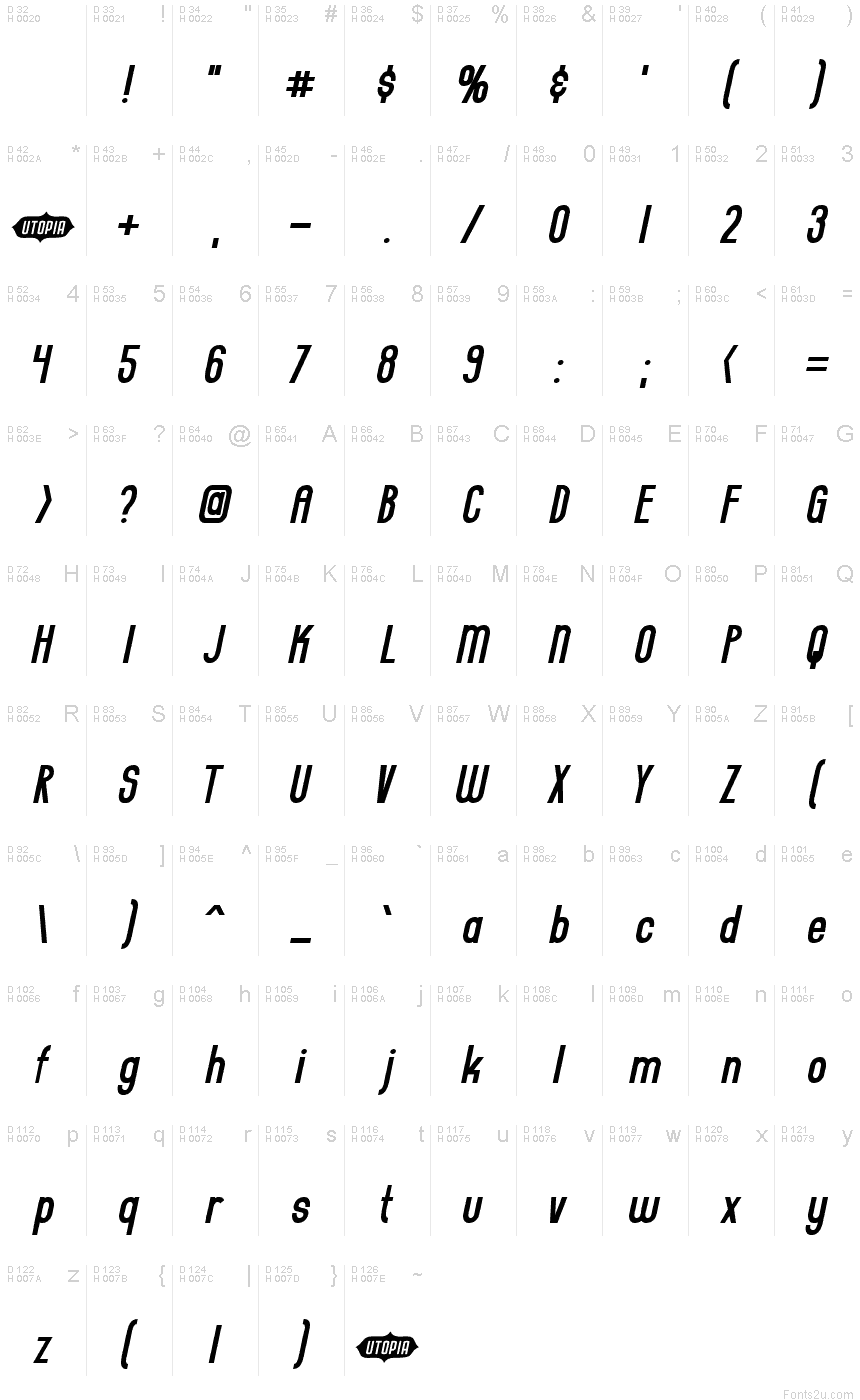
Everyday Formula Gaunt Sway
Everyday Formula Gaunt Sway od Utopiafonts to darmowy krój bezszeryfowy o ostrym, dynamicznym nachyleniu, który sprawia wrażenie, jakby był w ciągłym ruchu. Wysokie, smukłe litery i ciasna, pochylona do przodu postawa tworzą wrażenie dynamiki, jakby każde słowo pędziło pod wpływem silnego podmuchu wiatru. Kreski są czyste i pewne, co nadaje całości wyrazistą, mocną prezencję, która mimo to pozostaje lekka i nowoczesna.
Dzięki Everyday Formula Gaunt Sway nagłówki natychmiast zyskują na pilności i charakterze – świetnie sprawdzi się na plakatach, zinach, w grafice sportowej, na okładkach albumów, w odważnym brandingu oraz przy tworzeniu przyciągających wzrok grafik do mediów społecznościowych. Zredukowana szerokość sprawia, że długie tytuły mieszczą się w ciasnych miejscach bez utraty siły wyrazu, a spójny rytm zapewnia czytelność przy większych rozmiarach. Aby zachować równowagę, do tekstu głównego warto połączyć ten darmowy font z prostym, neutralnym krojem bezszeryfowym o mniejszej grubości.